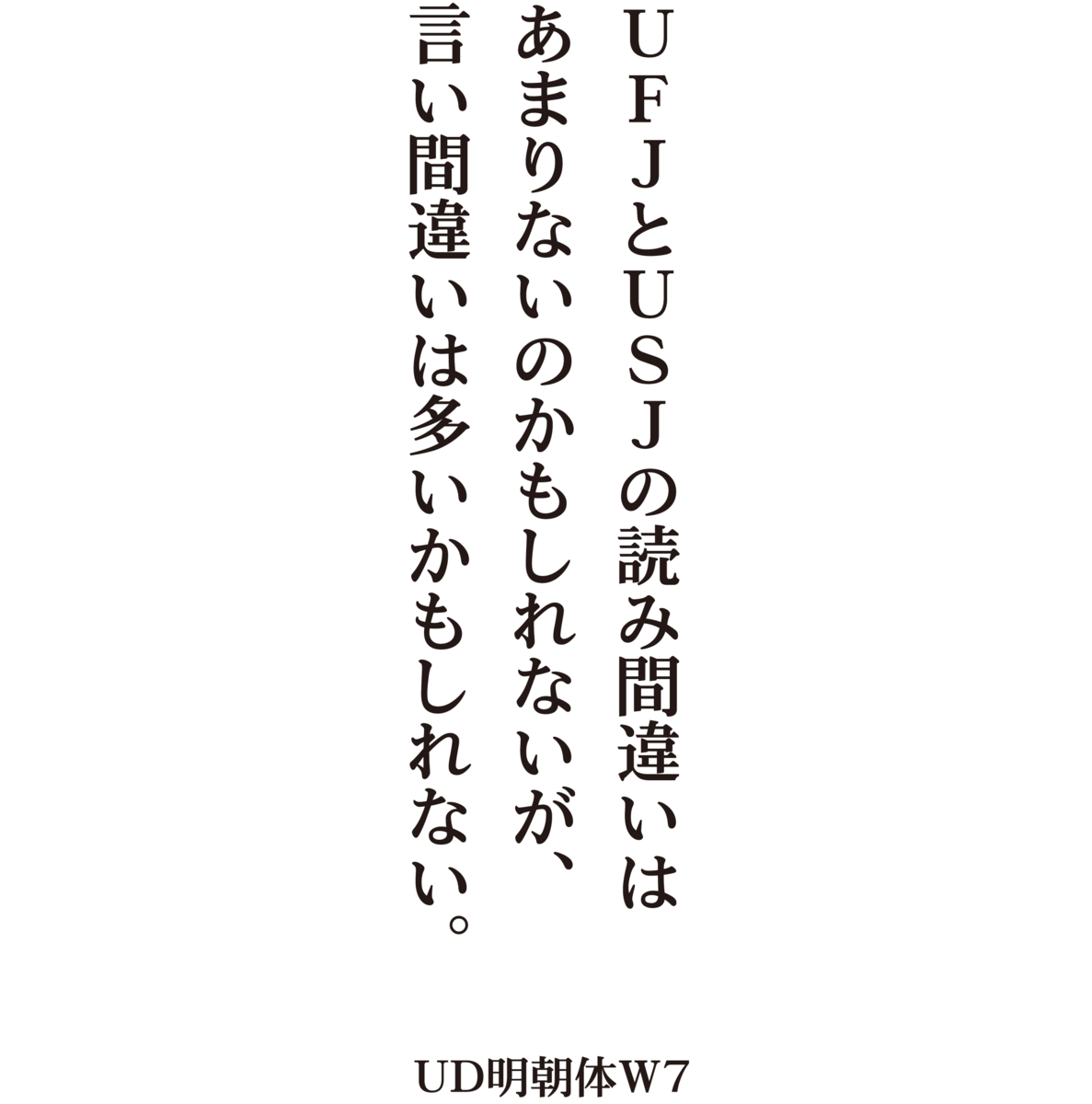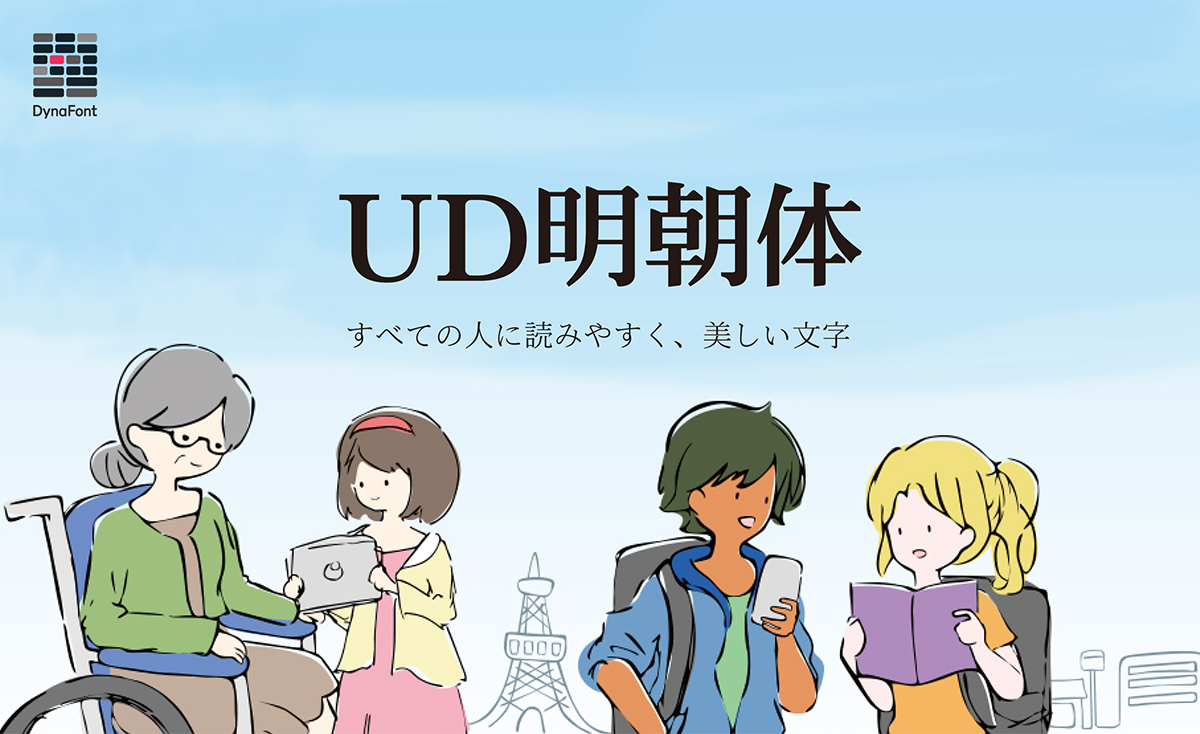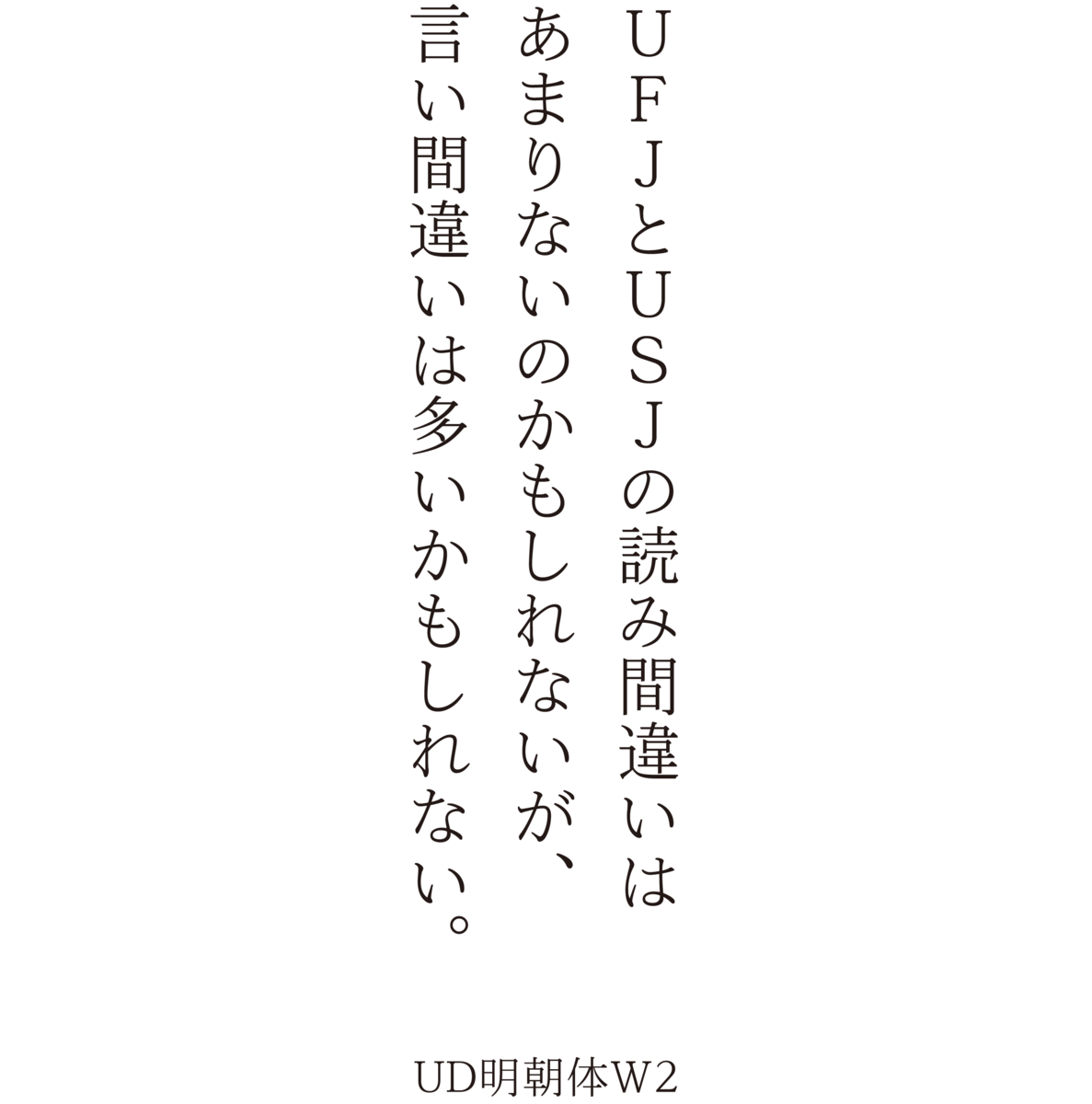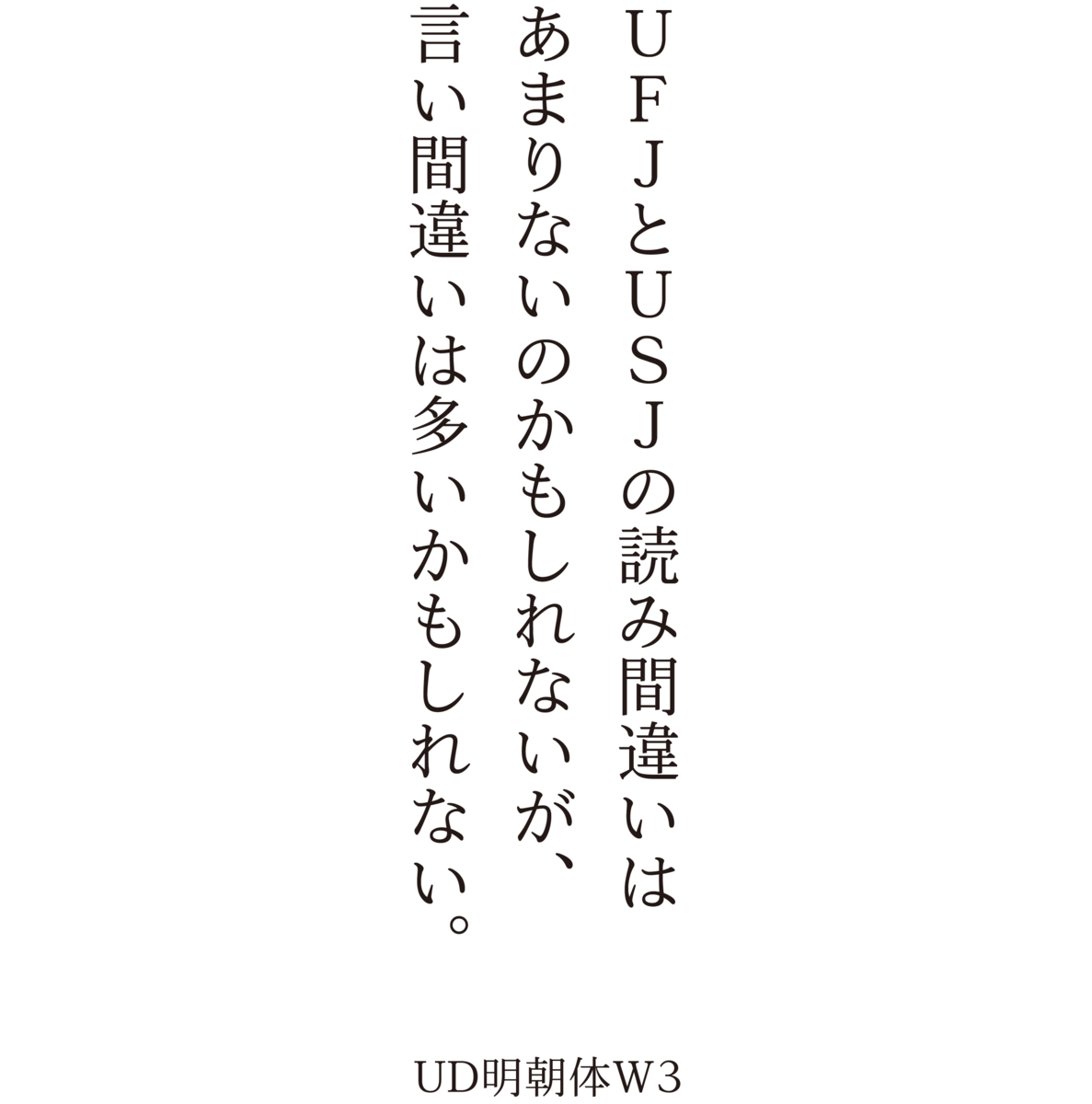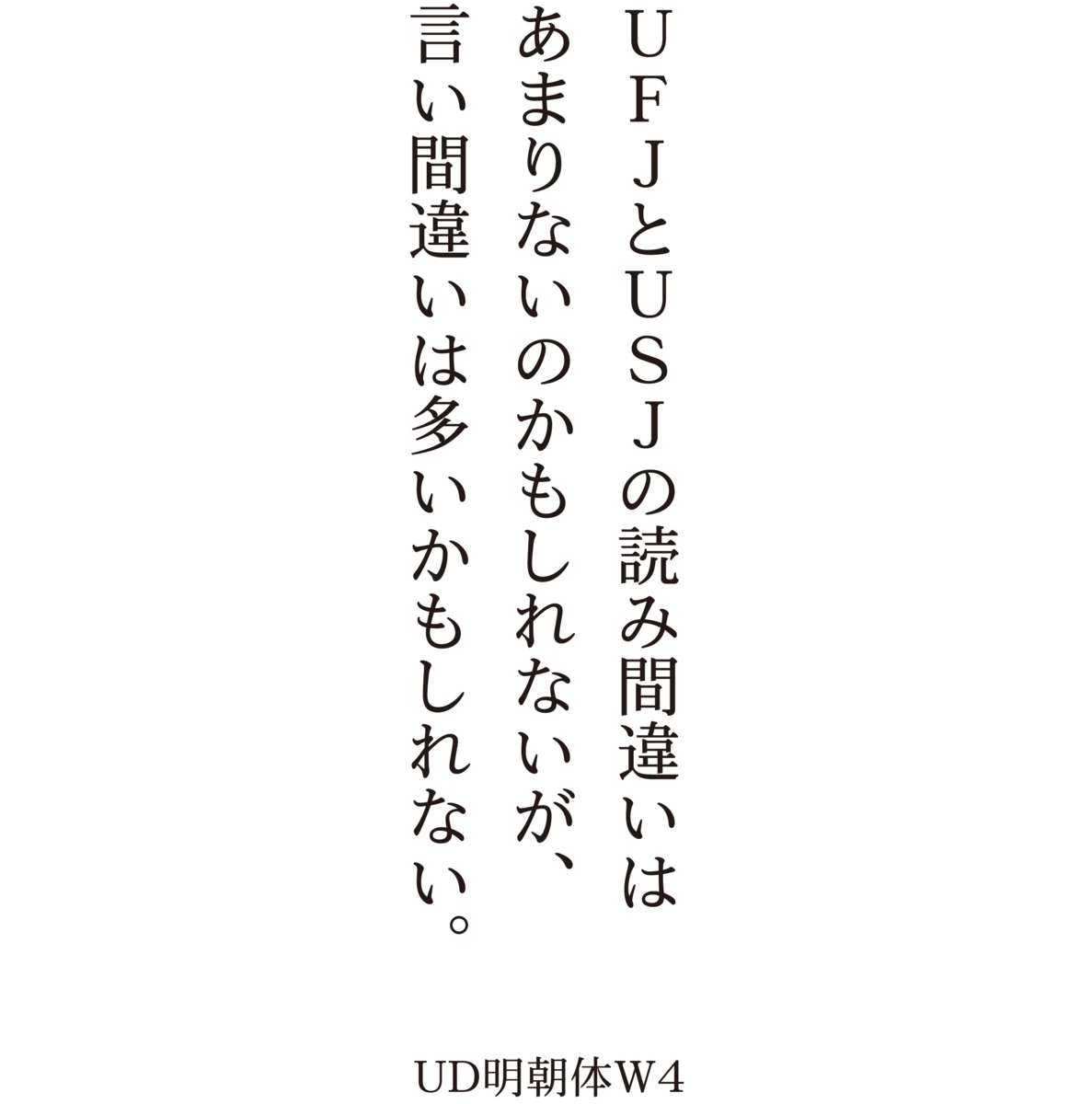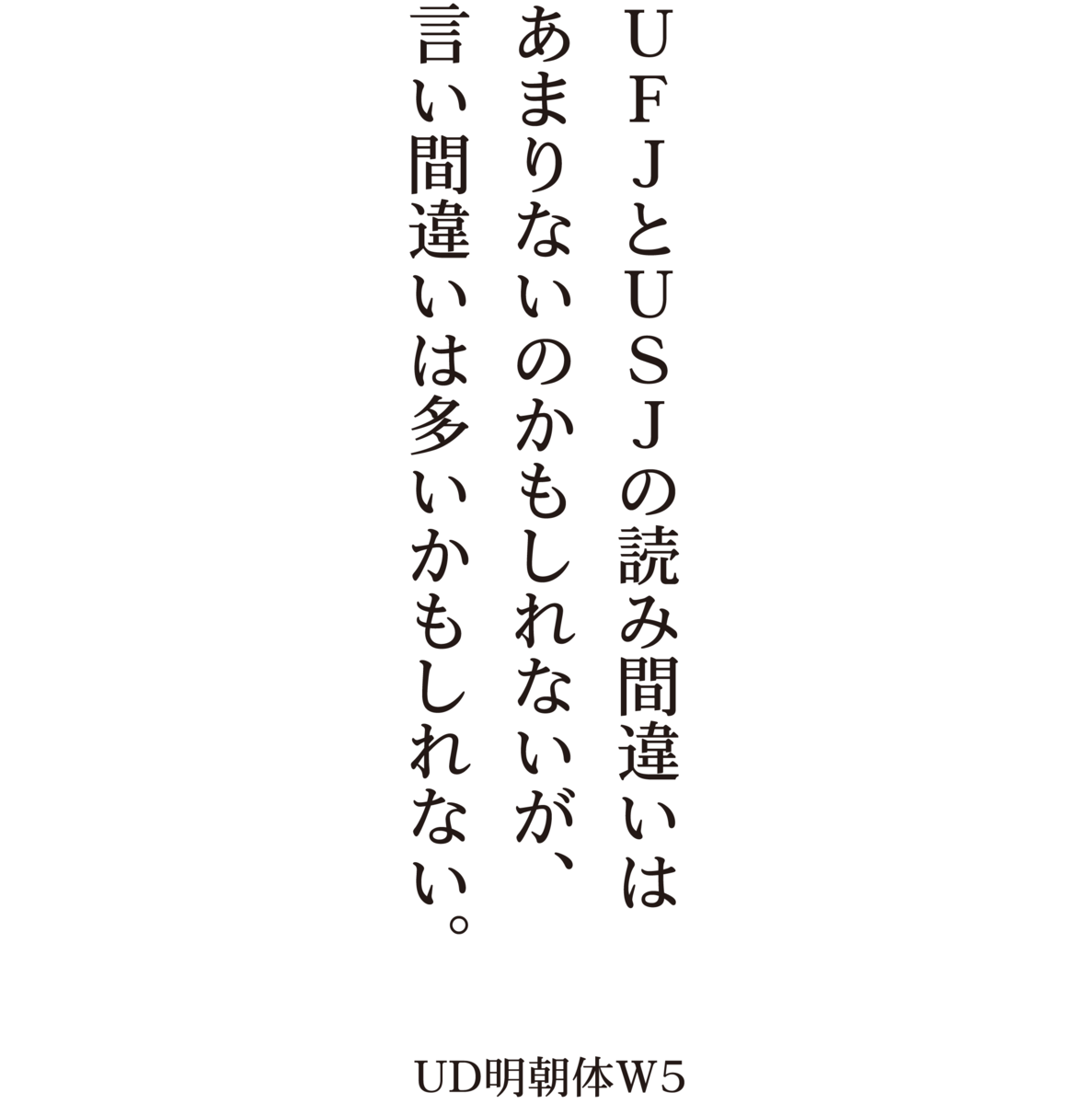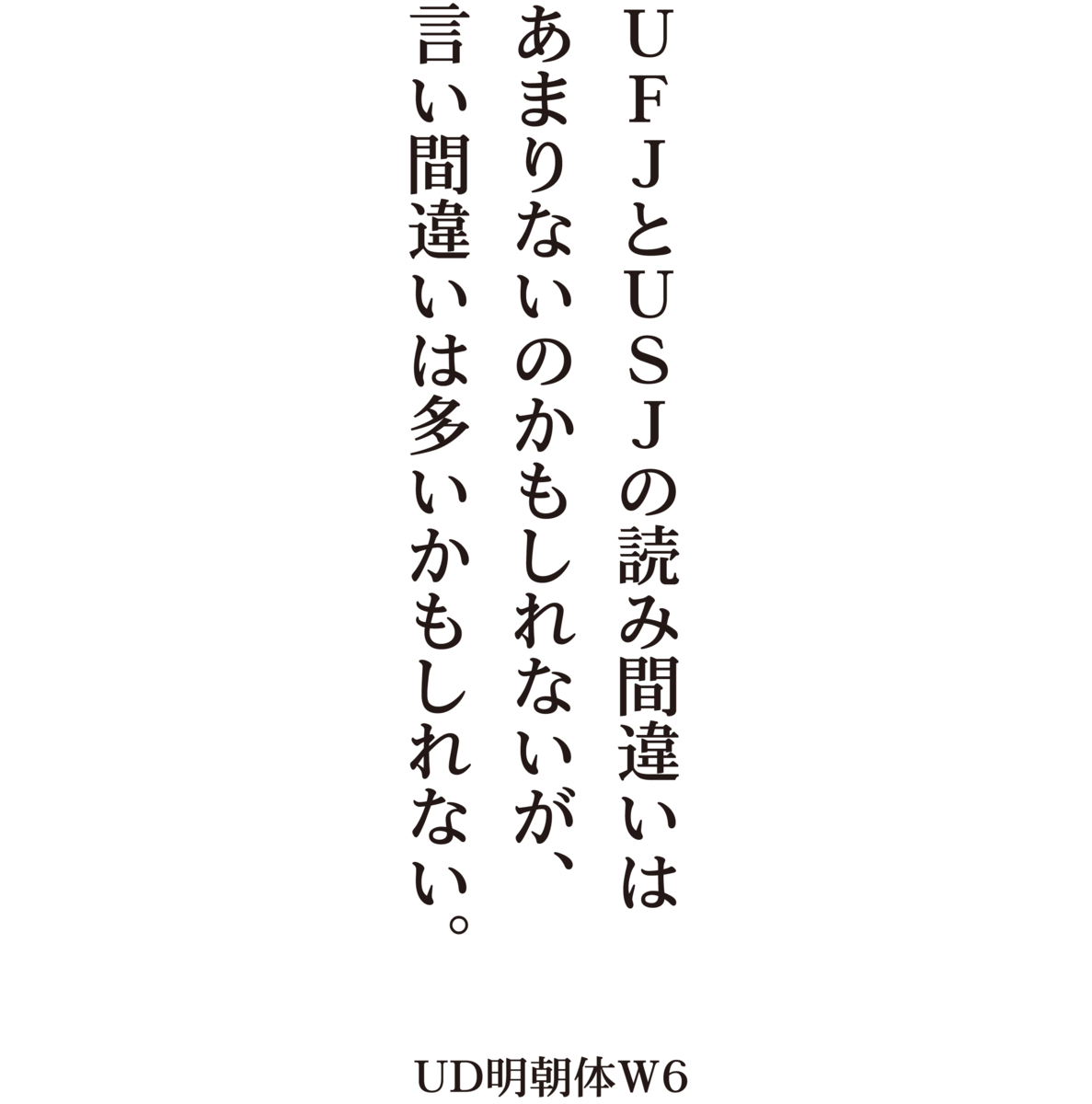
すべての人に読みやすく美しいUDフォント「UD明朝体」
UD明朝体は、ユニバーサルデザイン(UD)をコンセプトにした視認性と可読性を高めたユニバーサルデザインフォント(UDフォント/UD書体の明朝体。
高齢者や弱視(ロービジョン)の人を含めて全ての人が読みやすいように開発されており、W2、W3、W4、W5、W6、W7の6書体でファミリー展開している。
UD明朝体は、字面を大きく、ふところを広くし、読みやすさを追及。横線も太めではっきりと表示できる。アクセントを丸く処理することで、ちらつきや引っ掛かりがなく読みやすい。余計な装飾を省くことで文字がかすれにくい。UD明朝体は、字面を大きく、ふところを広くし、読みやすさを追及。横線も太めではっきりと表示できる。アクセントを丸く処理することで、ちらつきや引っ掛かりがなく読みやすい。余計な装飾を省くことで文字がかすれにくい。かなは起筆部をシンプルにし、エレメントの先端をまるく処理。
印刷での使用はもちろんのこと、各種デジタルデバイスから今や一人一台は手にしている小さな液晶画面での表示で使用する際も、シンプルではっきりとした印象を作り出すことができる。そのほか、ウェイトによる用途の違いを踏まえ、各ウェイトで字面の大きさを調整。太いウェイトは見出し向きで高い視認性が求められるため、字面を大き目に調整している。逆に細いウェイトは本文向きなので、字面を小さめにすることで、文字間が広がるので風通しが良く、より一層スムーズに読み進めることができる。
UD明朝体 書体見本